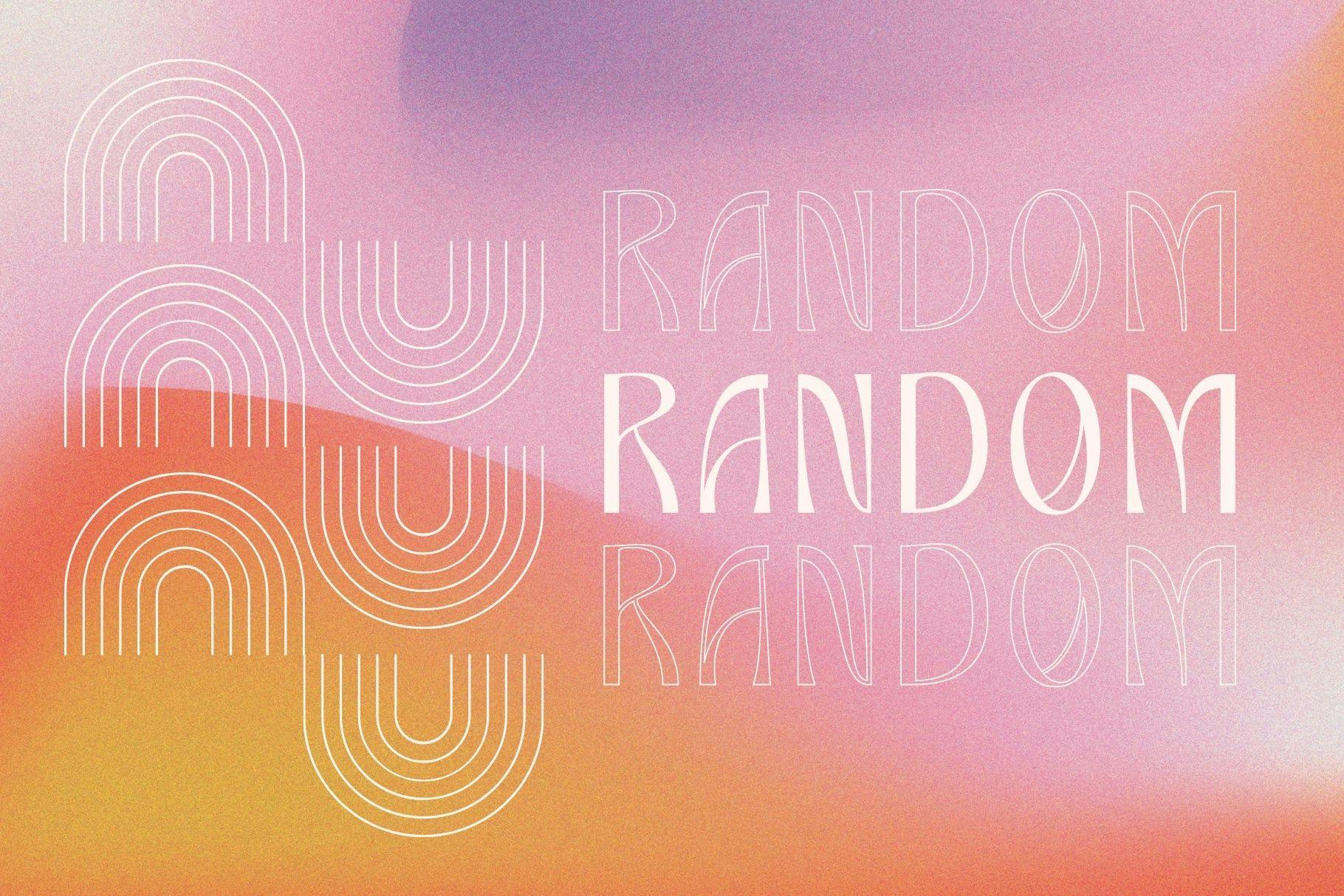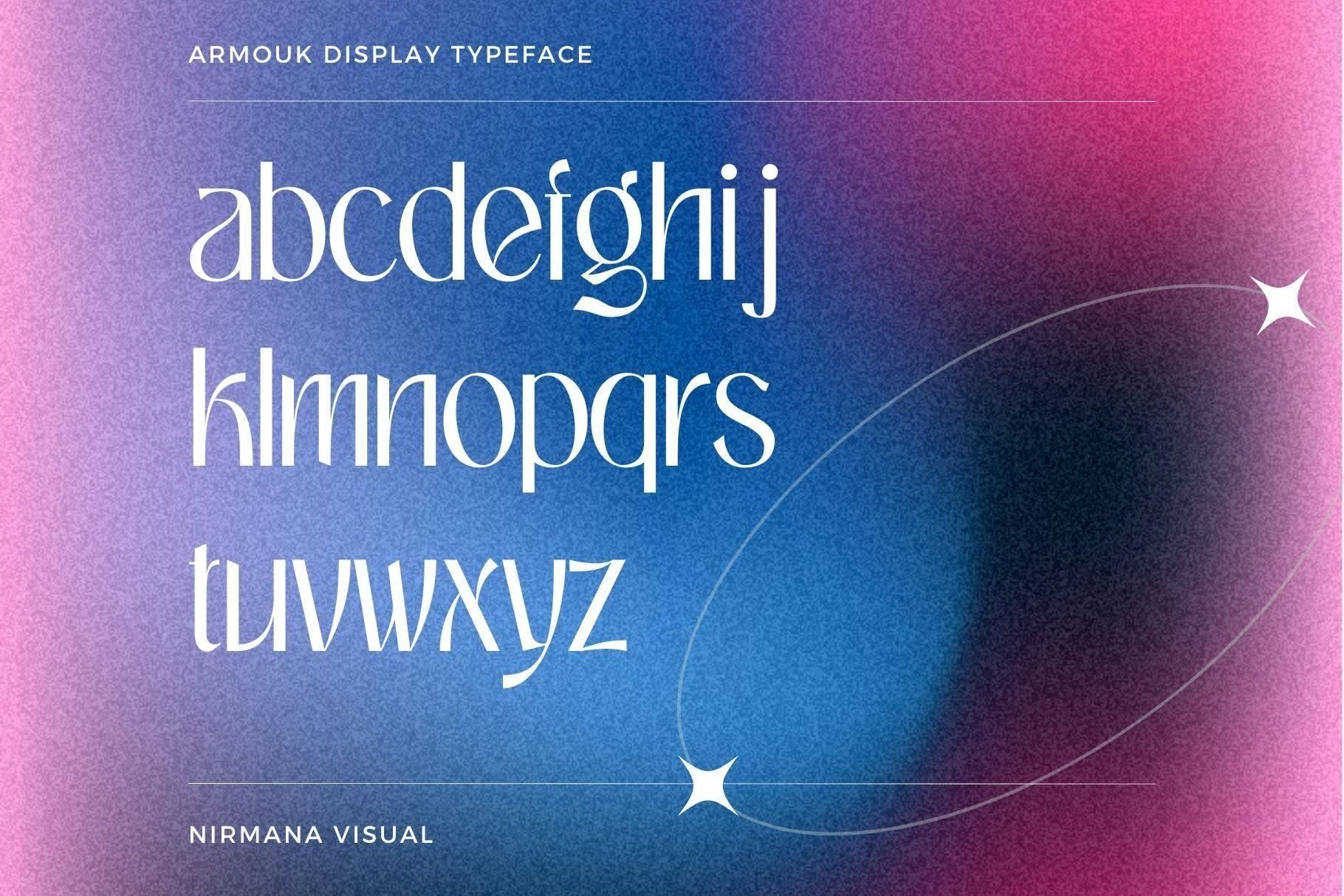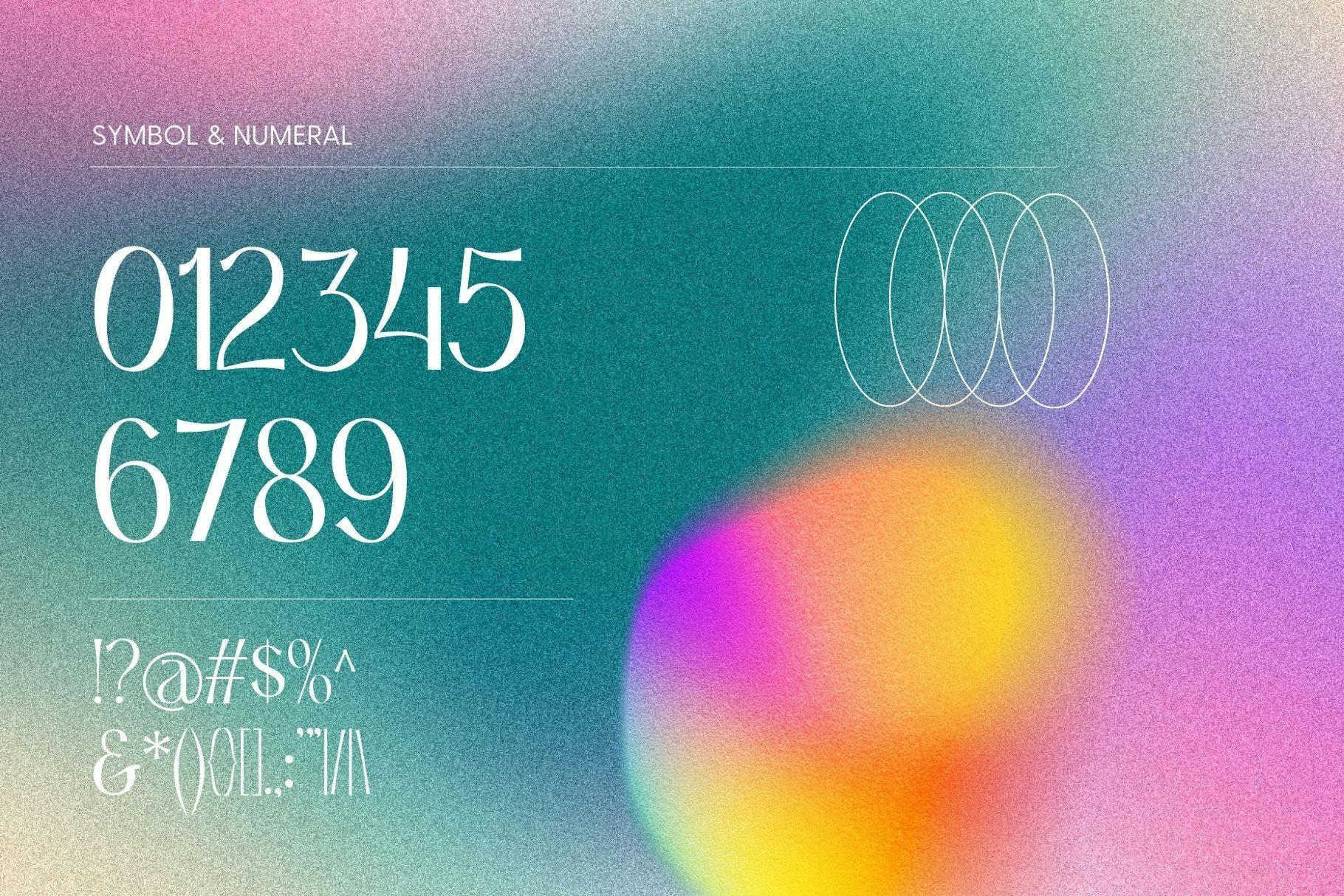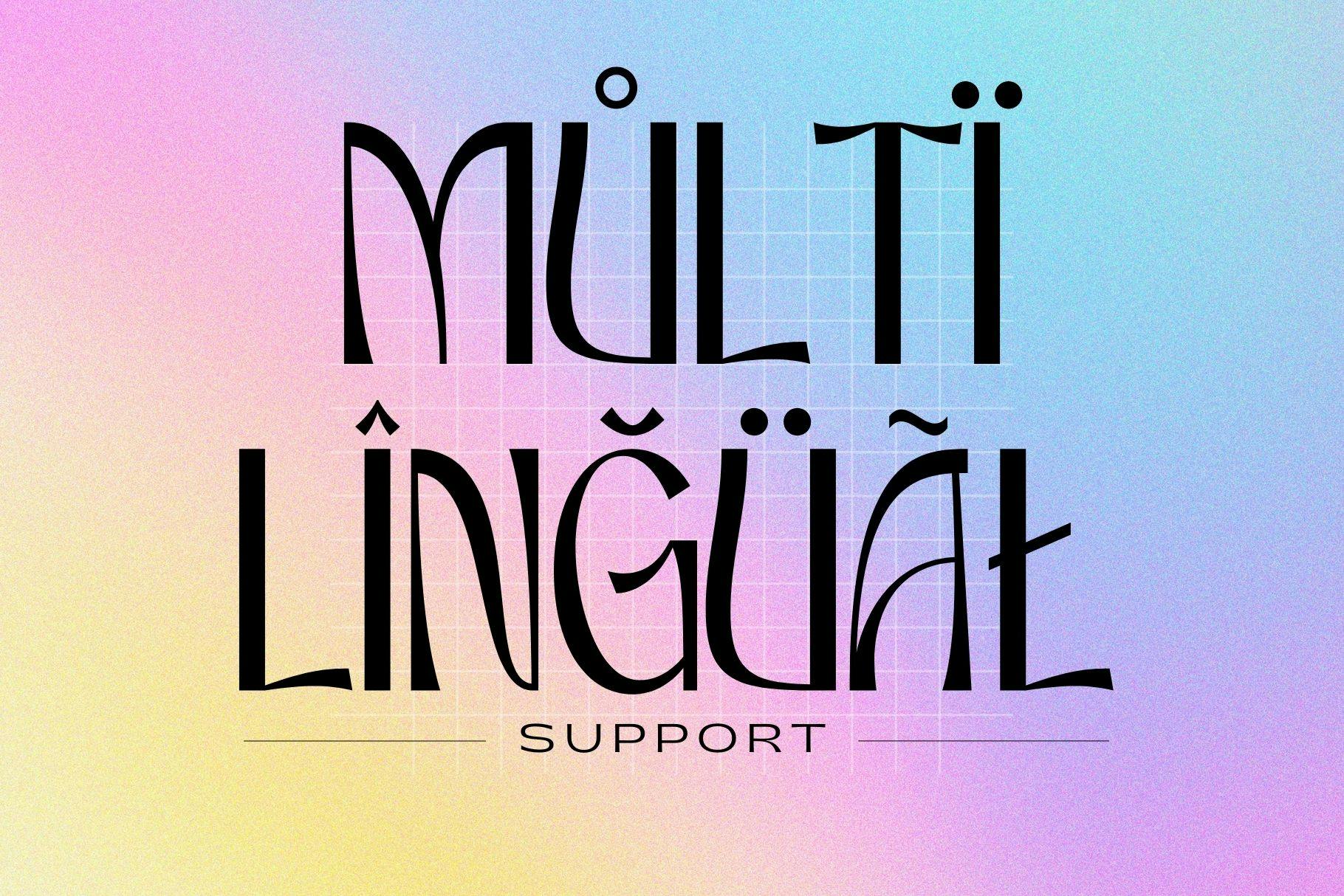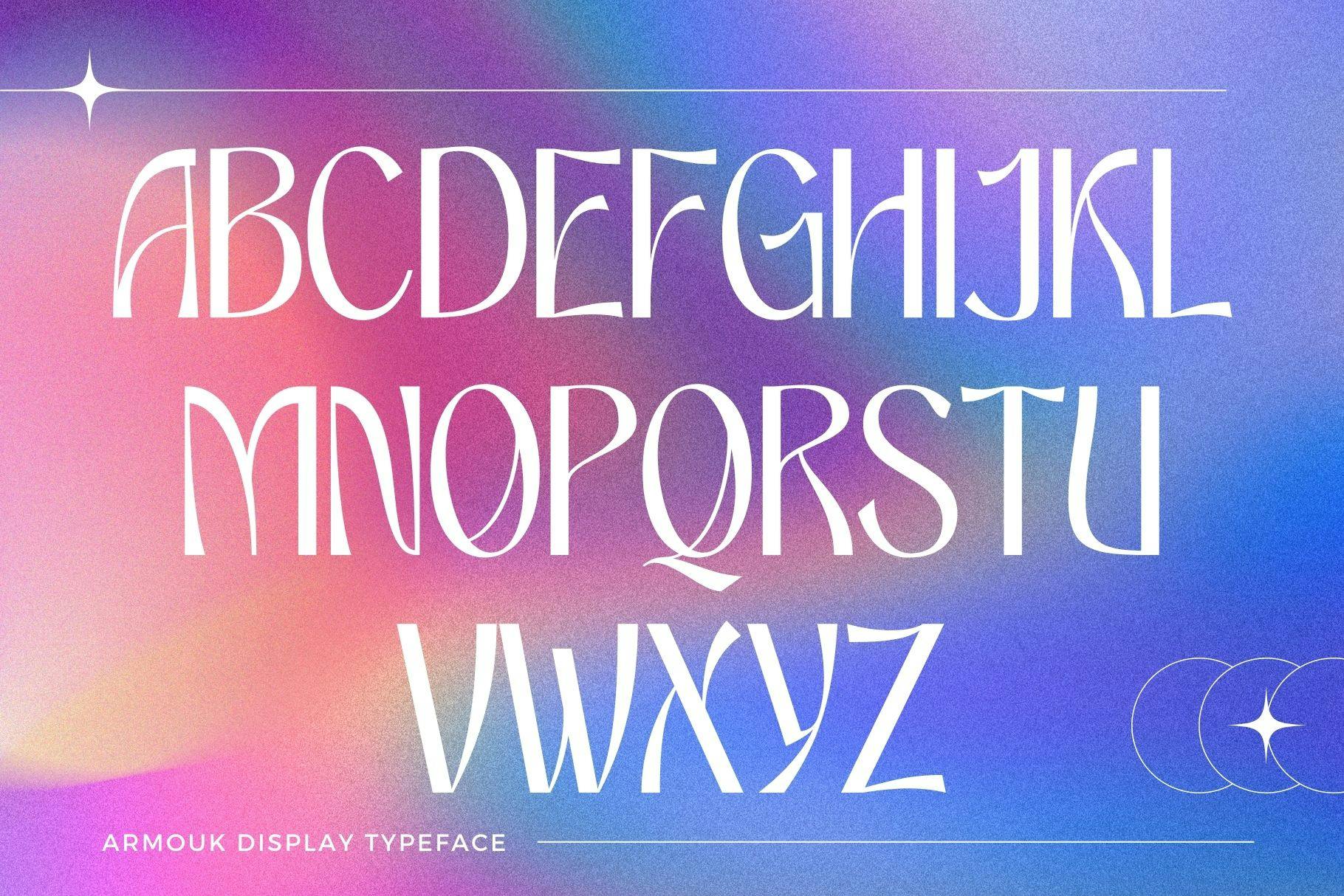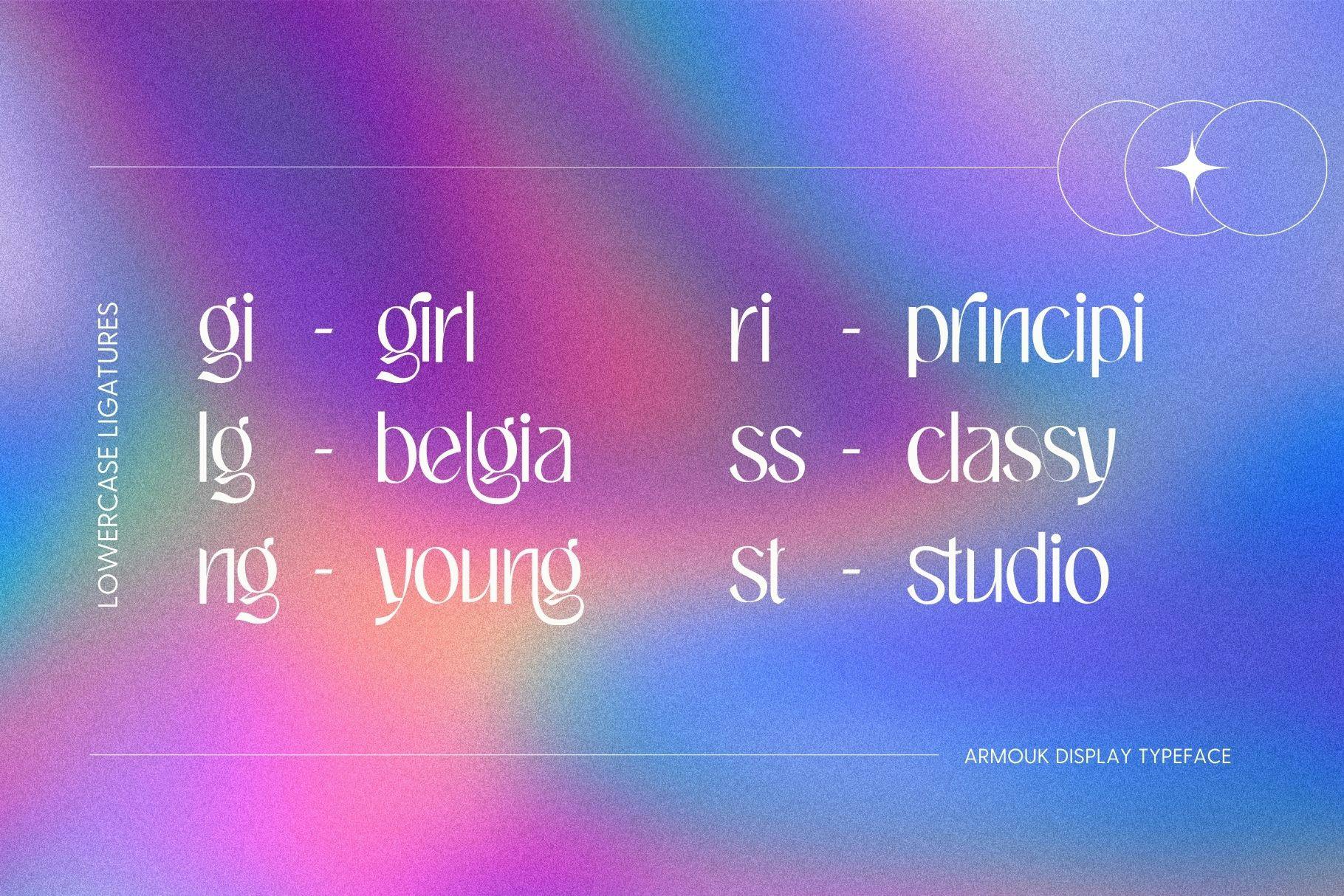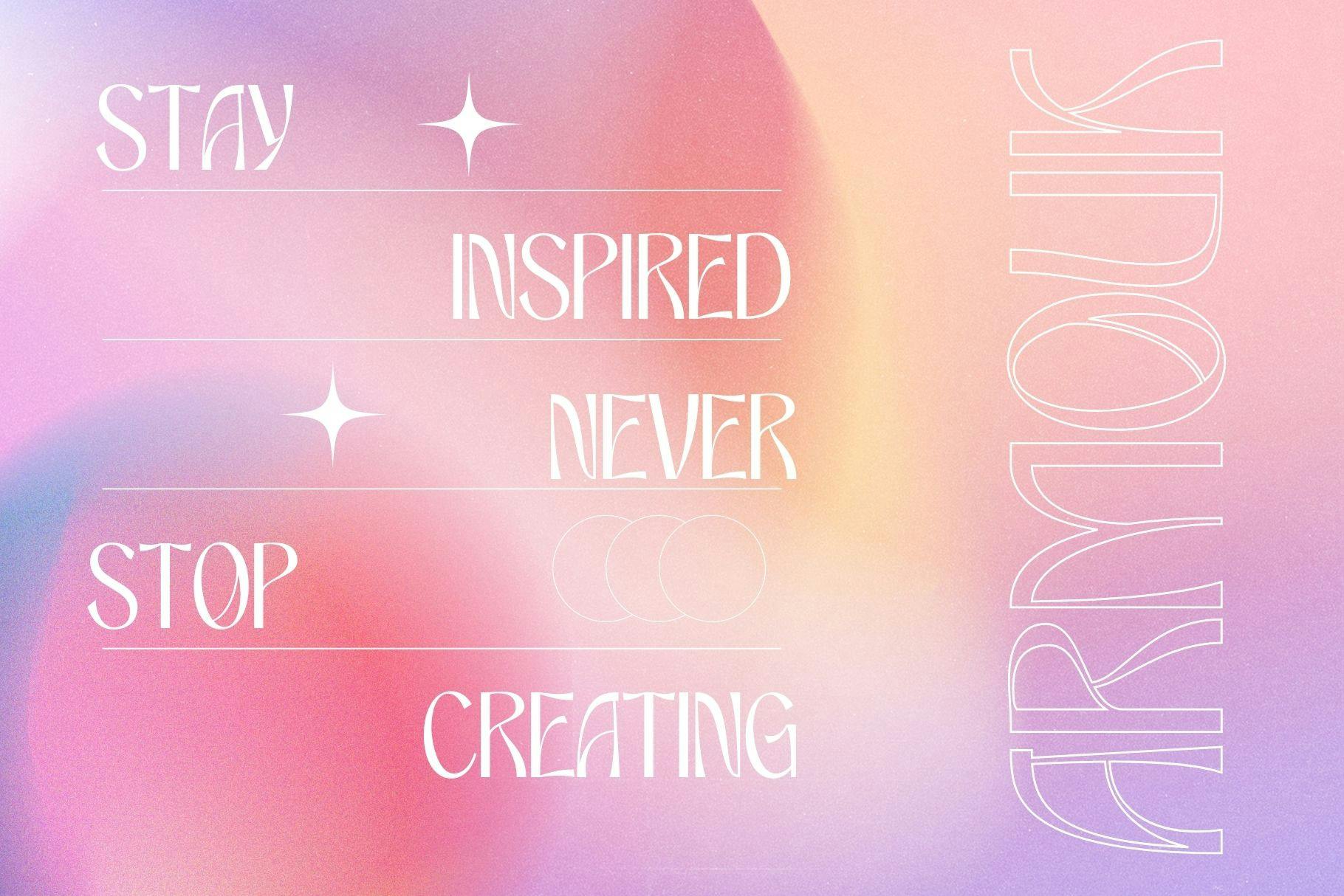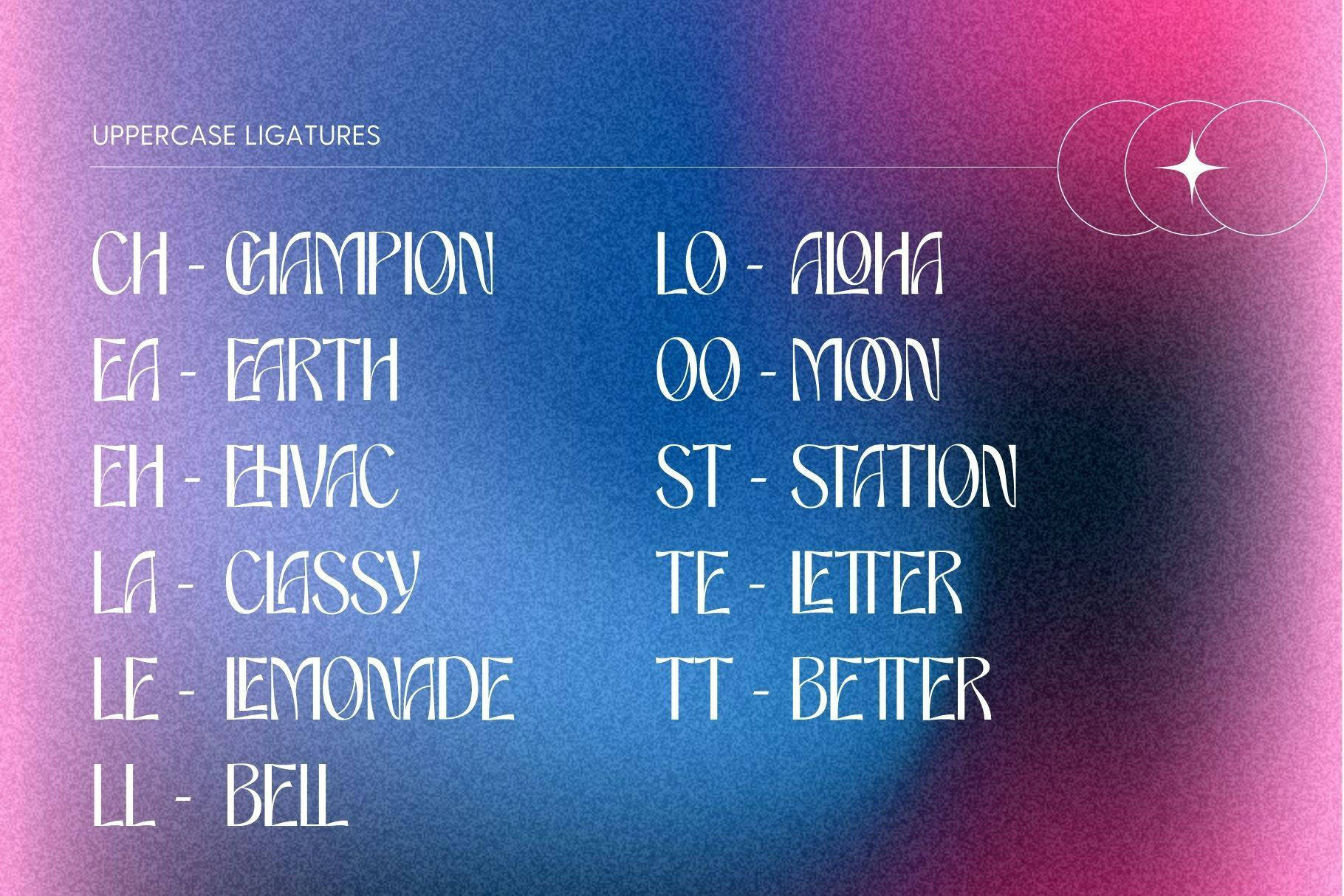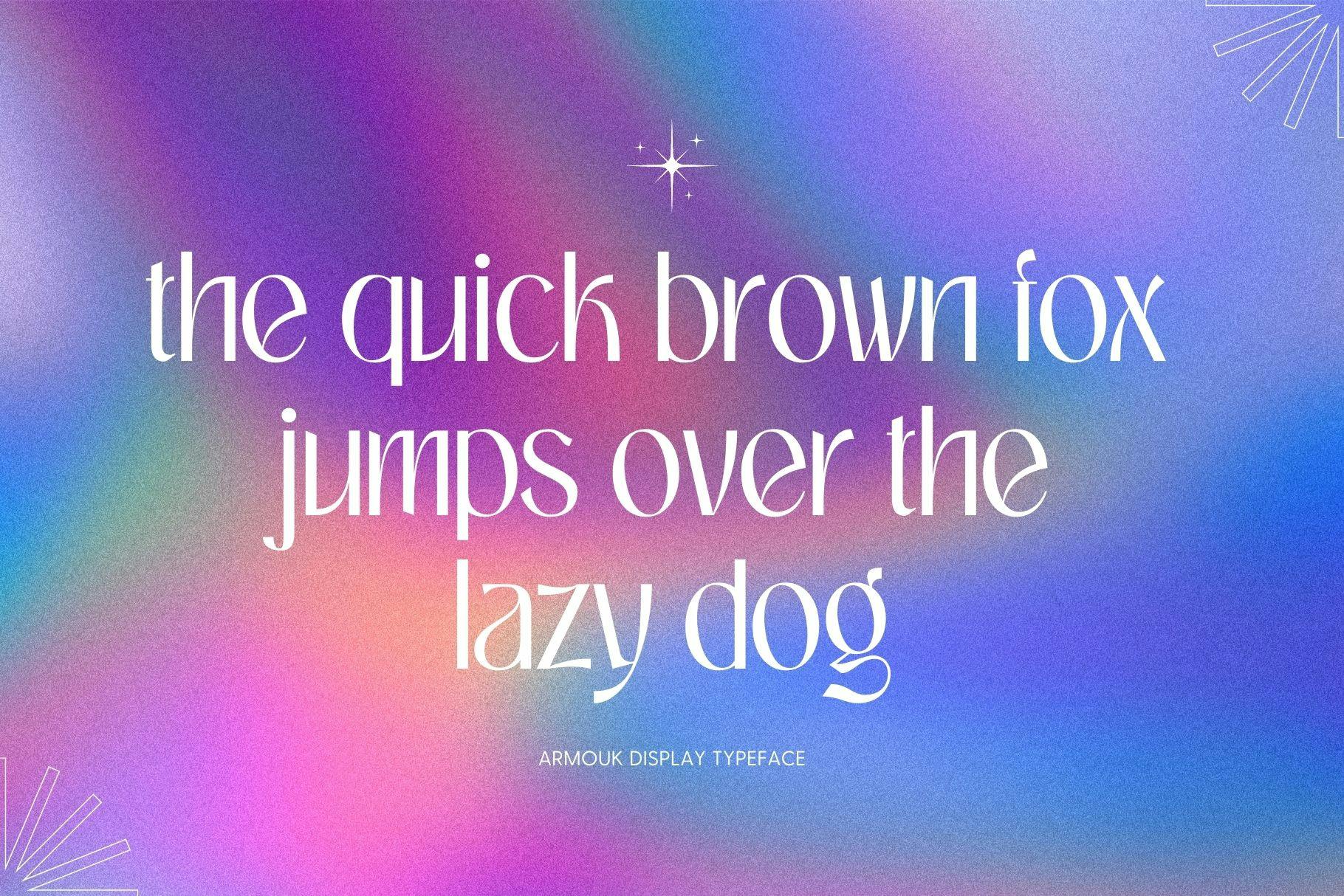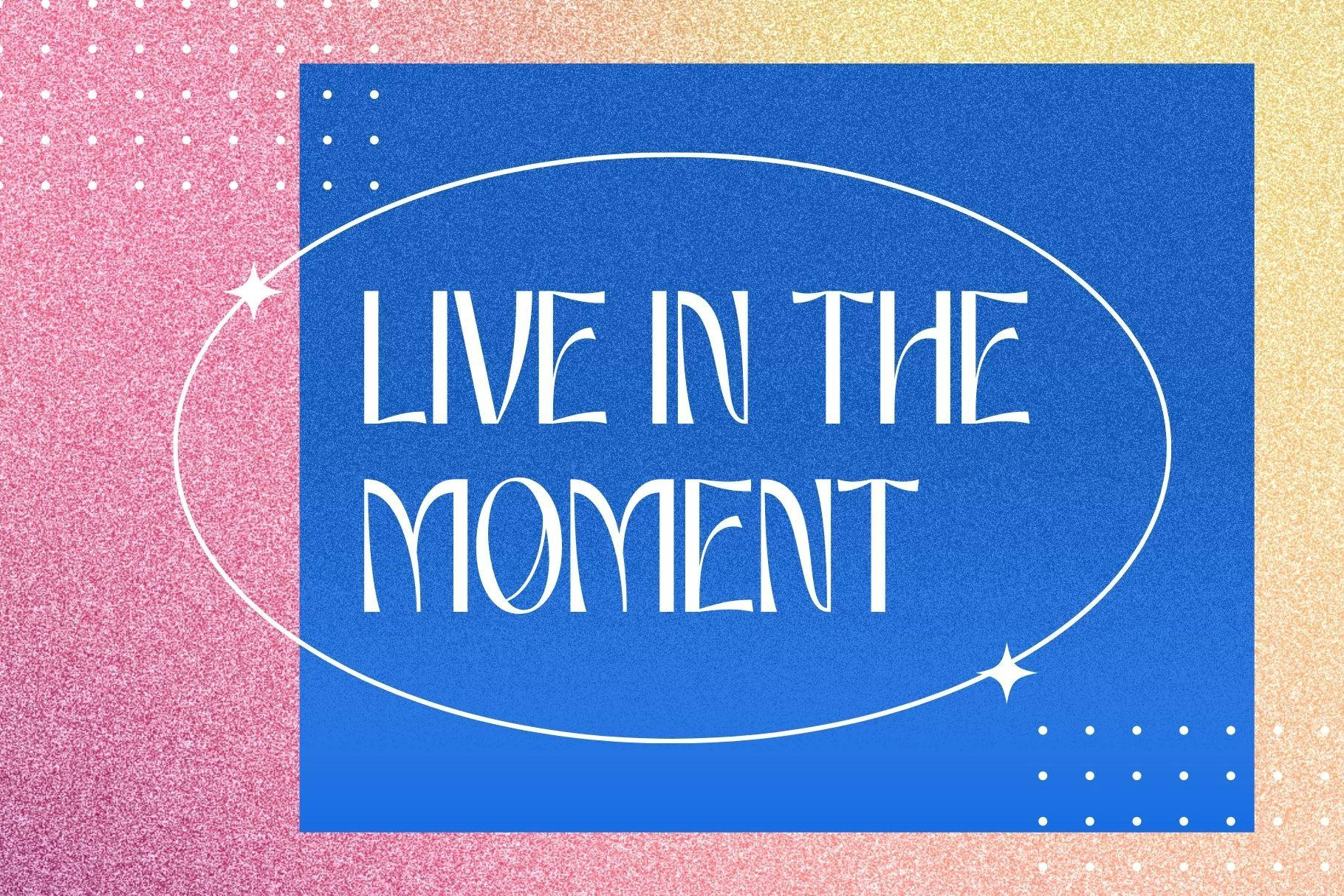
دانلود فونت لوگوی Armouk با طراحی مدرن
Armouk Logo Font
با فونت Armouk، طراحی‌های خود را به زیبایی بیفزایید.
Armouk، فونتی مدرن و از نوع Sans serif،
Armouk هارمونی زیبایی در تایپوگرافی برای پروژه‌های مختلف طراحی ارائه می‌دهد، از جمله لوگو و برندینگ، پست‌های رسانه‌های اجتماعی، تبلیغات و طراحی محصولات.